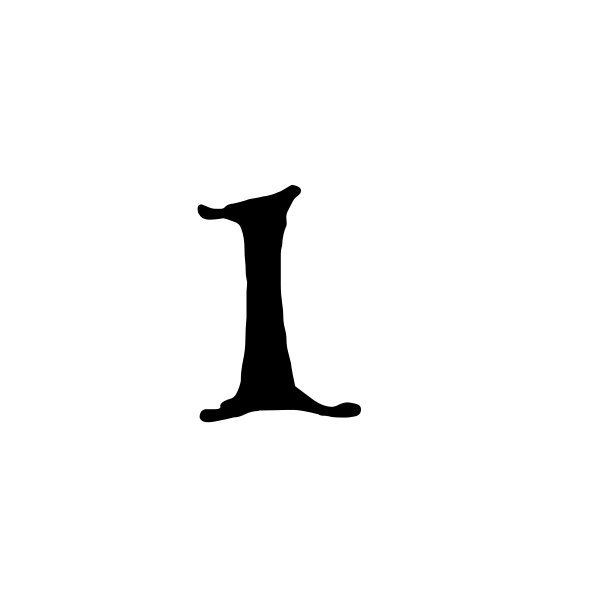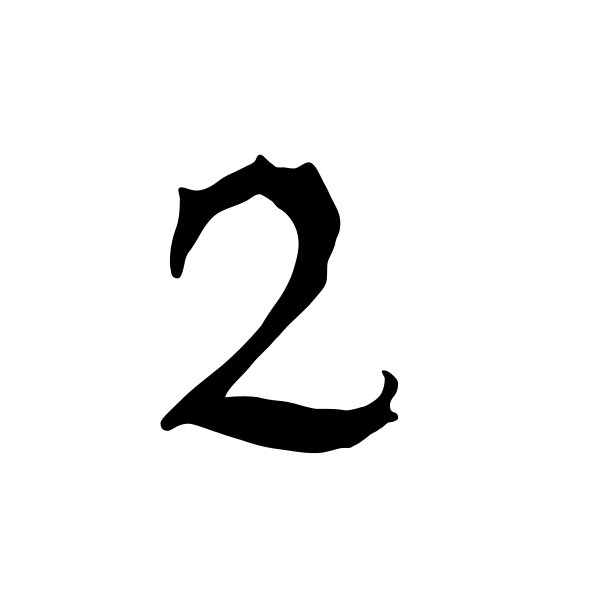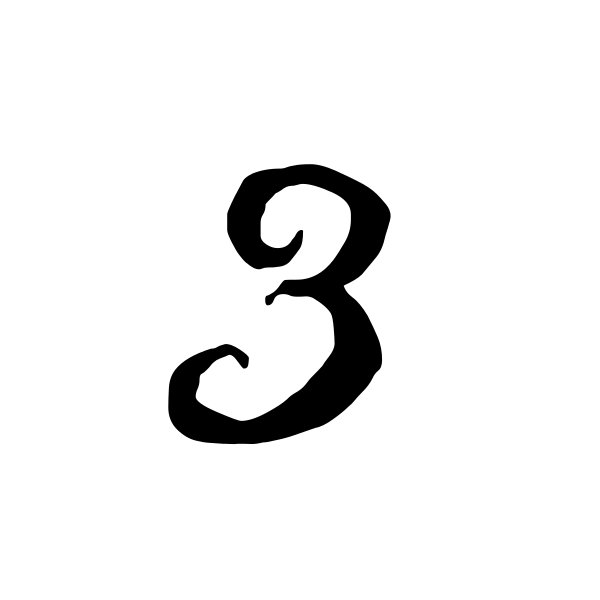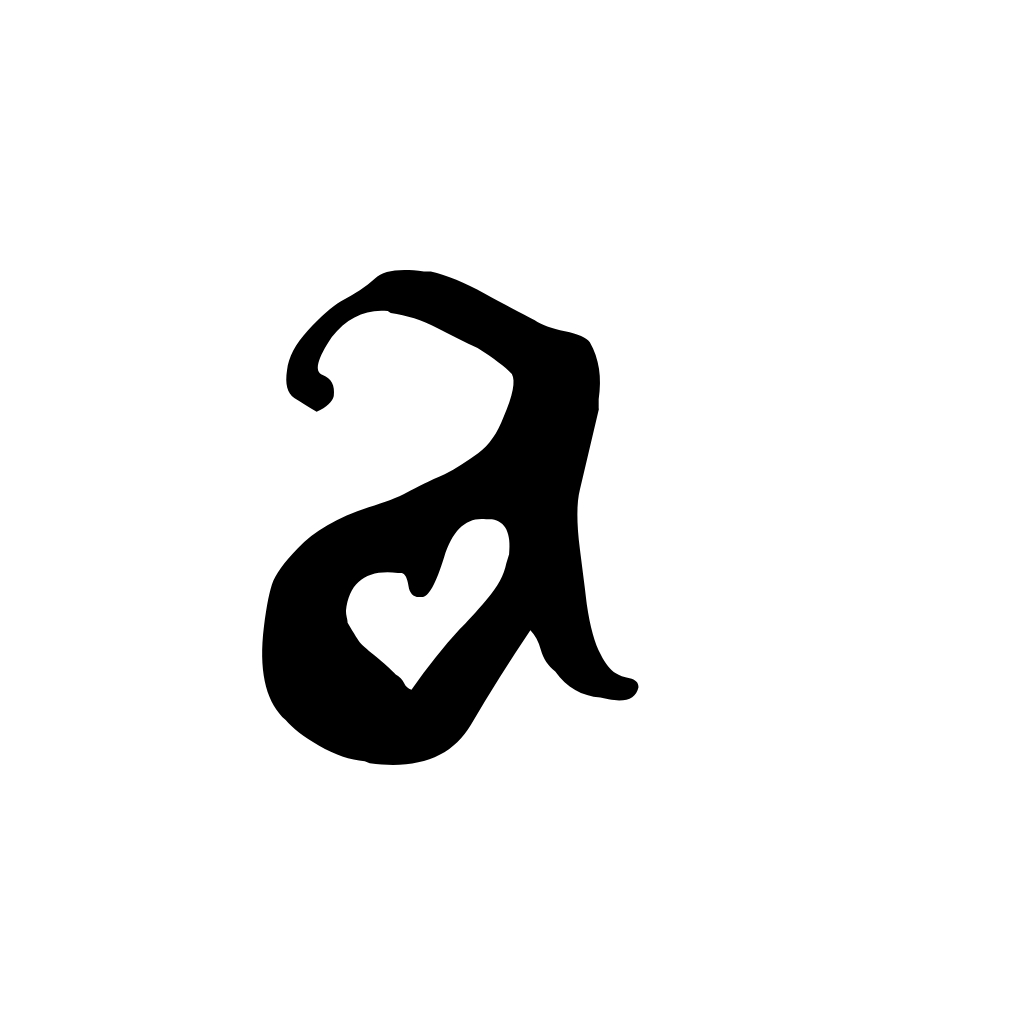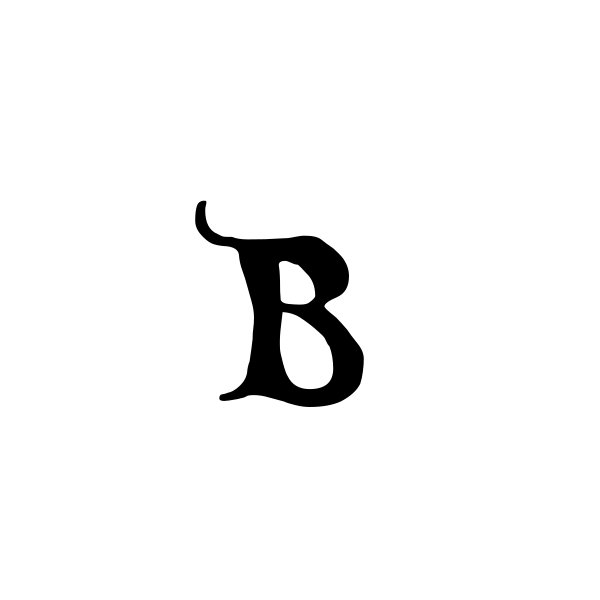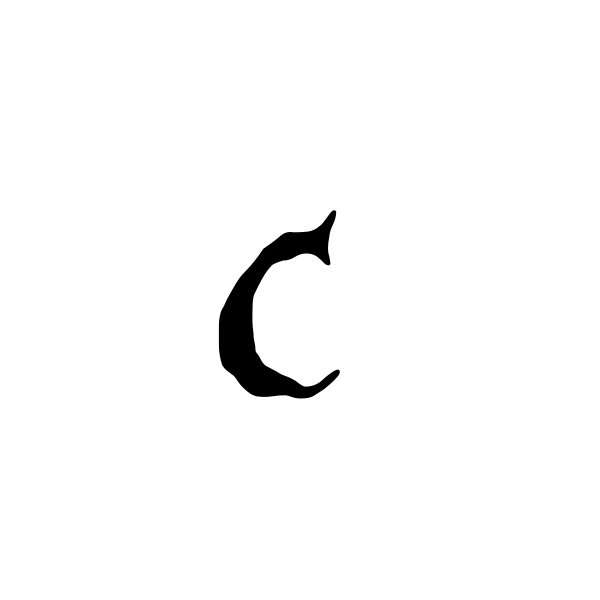
Little Fairy Magic Monogram Schriftart | Cricut-kompatibel
• Diese dekorative Little Fairy Magic Monogram Schrift im Märchen- und Storybook-Stil zeigt elegante, leicht verspielte Buchstabenformen, inspiriert von klassischen Fantasy-Illustrationen. Die Zeichen wirken lebendig mit sanften Rundungen, feinen Spitzen und einer handgezeichneten Optik, die Monogramm-Designs eine magische und fantasievolle Ausstrahlung verleiht. Grossbuchstaben sind ausdrucksstark gestaltet, während die Kleinbuchstaben denselben künstlerischen Stil beibehalten und so ein harmonisches und gut lesbares Gesamtbild für Monogramm-Projekte schaffen.
• Die Schrift enthält Gross- und Kleinbuchstaben sowie die Zahlen 0–9 und eignet sich dadurch für viele kreative Anwendungen. Besonders für Monogramm-Designs, dekorative Titel, personalisierte Projekte und thematische Bastelarbeiten ist dieser Stil ideal, wenn eine märchenhafte oder fantasievolle Atmosphäre gewünscht ist. Die Buchstaben lassen sich sauber schneiden und behalten ihre feinen Details, sodass das fertige Design den einzigartigen, illustrierten Storybook-Look der Monogramm-Schrift beibehält.